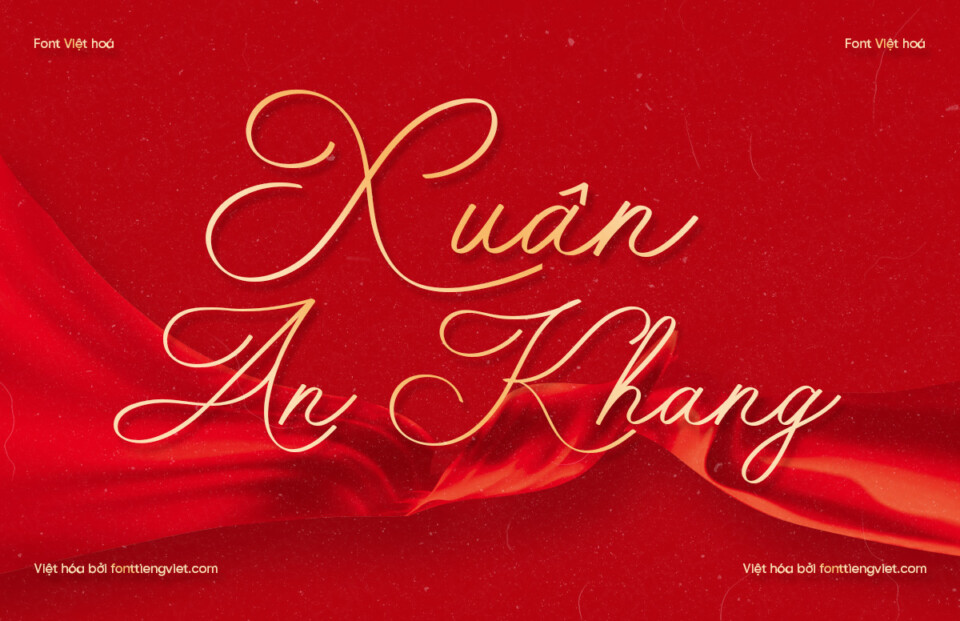
Font Việt hoá 1FTV VIP Neraly Font tết
Giới thiệu về bộ Font Việt hoá 1FTV VIP Neraly Font tết
Trong không khí rộn ràng của những ngày cuối năm, việc tìm kiếm một bộ Font Miễn Phí chất lượng để phục vụ thiết kế là nhu cầu thiết yếu của các bạn học sinh và giáo viên. Bộ Font Việt hoá 1FTV VIP Neraly Font tết nổi lên như một sự lựa chọn hoàn hảo nhờ phong cách thiết kế hiện đại nhưng vẫn giữ được nét truyền thống đặc trưng của văn hóa Việt Nam. Đây là mẫu chữ được tinh chỉnh kỹ lưỡng về dấu tiếng Việt, giúp người dùng không còn lo lắng về lỗi hiển thị khi đánh văn bản trên các phần mềm đồ họa hay ứng dụng soạn thảo thông thường. Với đường nét thanh thoát và sự kết hợp độc đáo, bộ font này hứa hẹn sẽ mang đến luồng gió mới cho các ấn phẩm Tết của bạn.
Đặc điểm nổi bật của Font Việt hoá 1FTV VIP Neraly Font tết
Sức hút của bộ chữ này nằm ở sự linh hoạt và tính thẩm mỹ cao, phù hợp với nhiều loại hình trình bày khác nhau. Dưới đây là những lý do bạn nên sở hữu ngay bộ font này trong bộ sưu tập cá nhân của mình.
Thiết kế đậm chất lễ hội
Mẫu Font Việt hoá 1FTV VIP Neraly Font tết sở hữu những đường cong mềm mại, gợi liên tưởng đến những nét vẽ thư pháp uyển chuyển. Độ dày của các nét chữ được tính toán tỉ mỉ để tạo ra sự cân bằng, giúp nội dung trở nên nổi bật trên các nền màu đỏ hoặc vàng truyền thống của ngày Tết. Đặc biệt, bộ chữ này rất dễ đọc, phù hợp cho cả tiêu đề lẫn các đoạn văn bản ngắn, giúp thông điệp chúc mừng năm mới của các bạn học sinh gửi đến thầy cô và gia đình trở nên trang trọng hơn.
Khả năng ứng dụng đa dạng
Không chỉ giới hạn trong các tấm thiệp, Font Việt hoá 1FTV VIP Neraly Font tết còn cực kỳ hữu dụng trong việc thiết kế băng rôn nhà trường, bảng tin lớp học hay các clip trình chiếu văn nghệ. Các bạn có thể sử dụng font chữ này để trang trí ảnh bìa Facebook, làm banner cho trang web hoặc thậm chí là in ấn trên bao lì xì tự thiết kế. Sự đồng nhất trong bộ mã tiếng Việt giúp việc soạn thảo nội dung trở nên nhanh chóng và chuyên nghiệp hơn bao giờ hết.
Lời kết cho thiết kế Tết của bạn